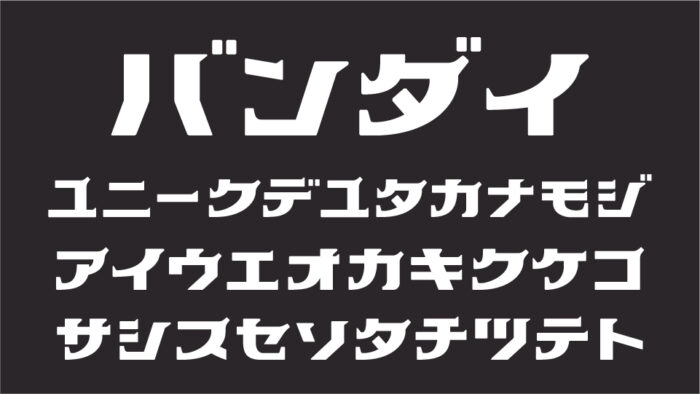
万代スポーツ
万代スポーツフォントは、町で見かけた看板や店名の個性的で味のある文字をフォント化するプロジェクト「のらもじ発見プロジェクト」で作られたカタカナフォントです。
スポーツ用品を扱うお店の店名ロゴですが、ウェイトがあり力強いフォルムですが、ぴょこっとした飾りが上品な可愛さがあるデザインがとても素敵なフォントです。
収録文字は、カタカナ・記号が収録されています。